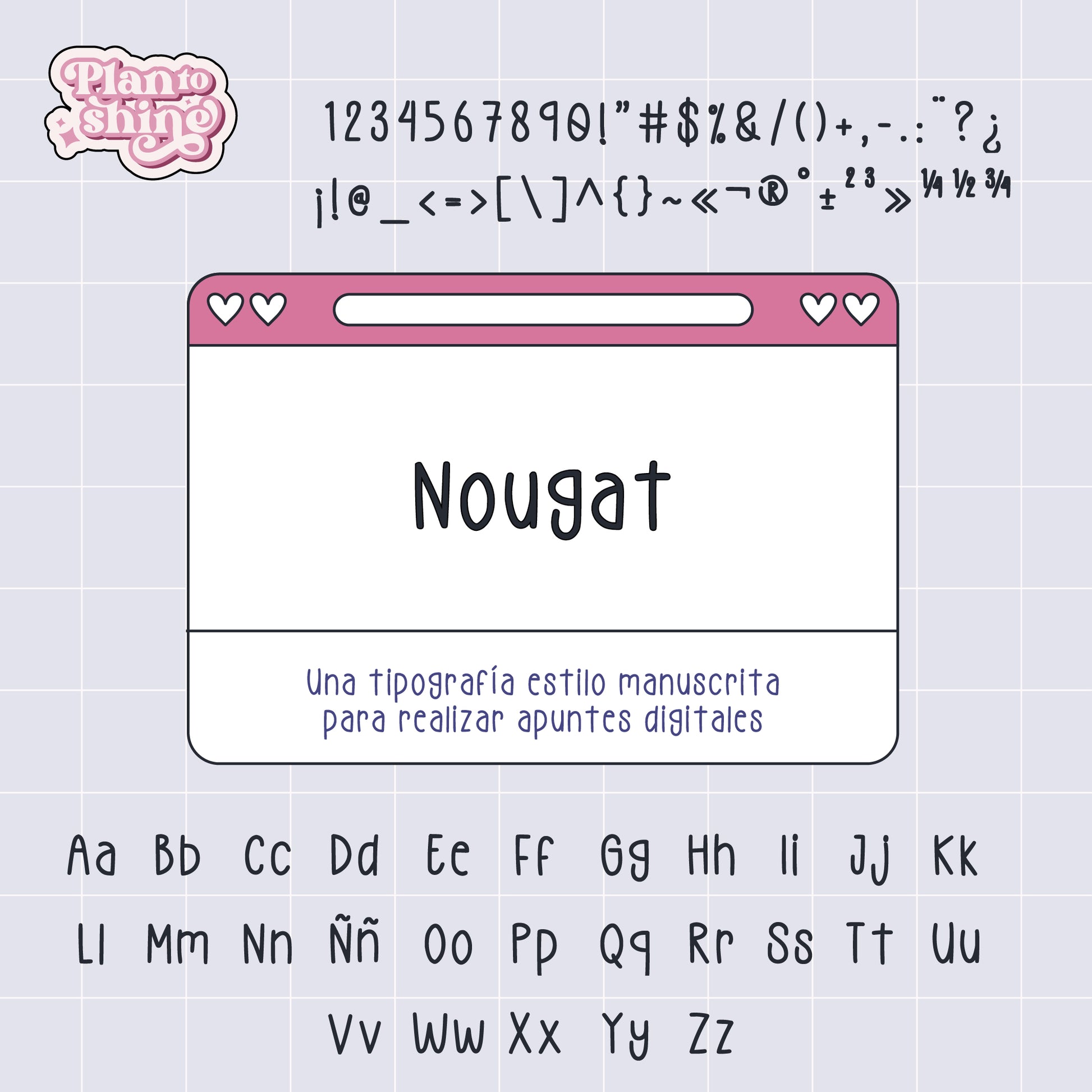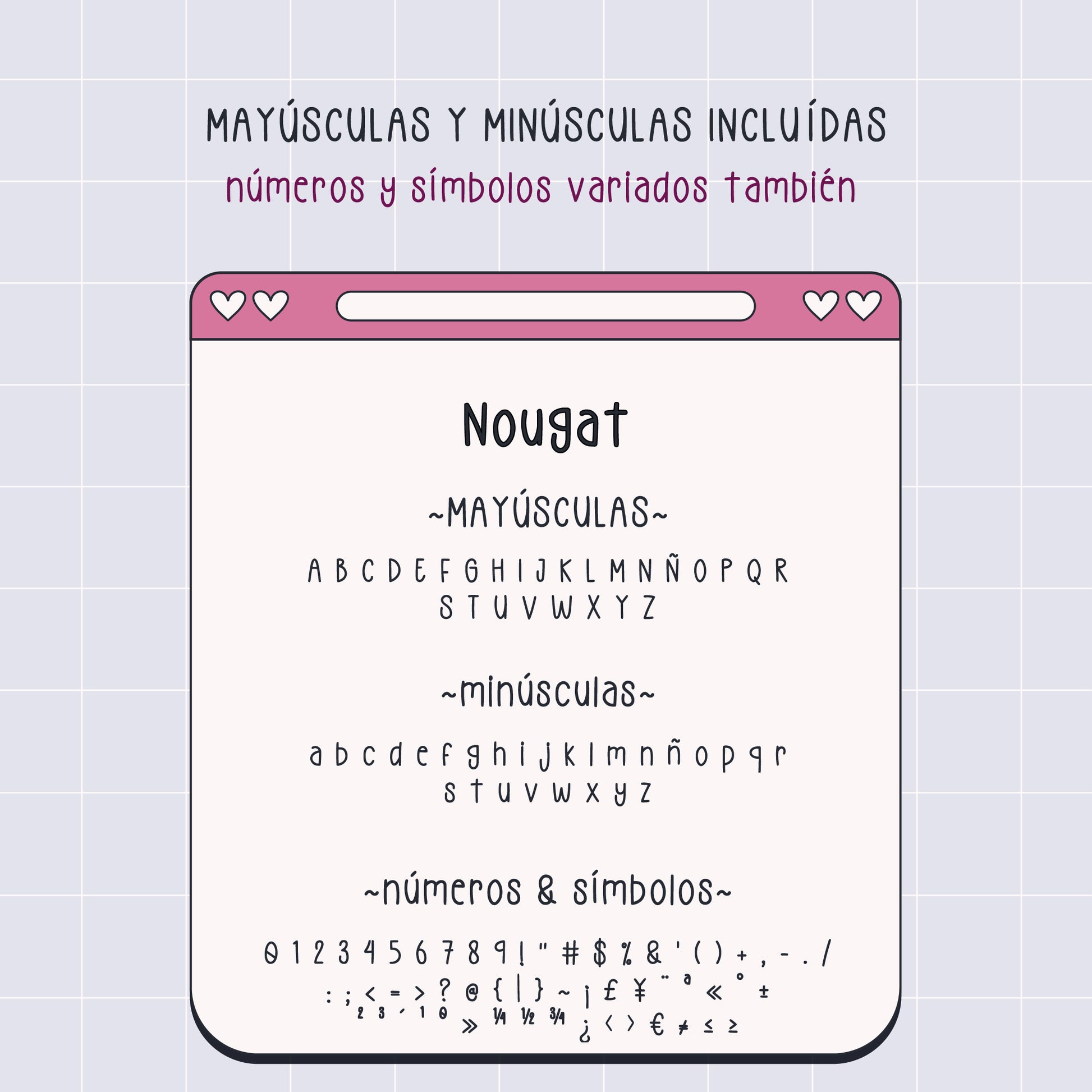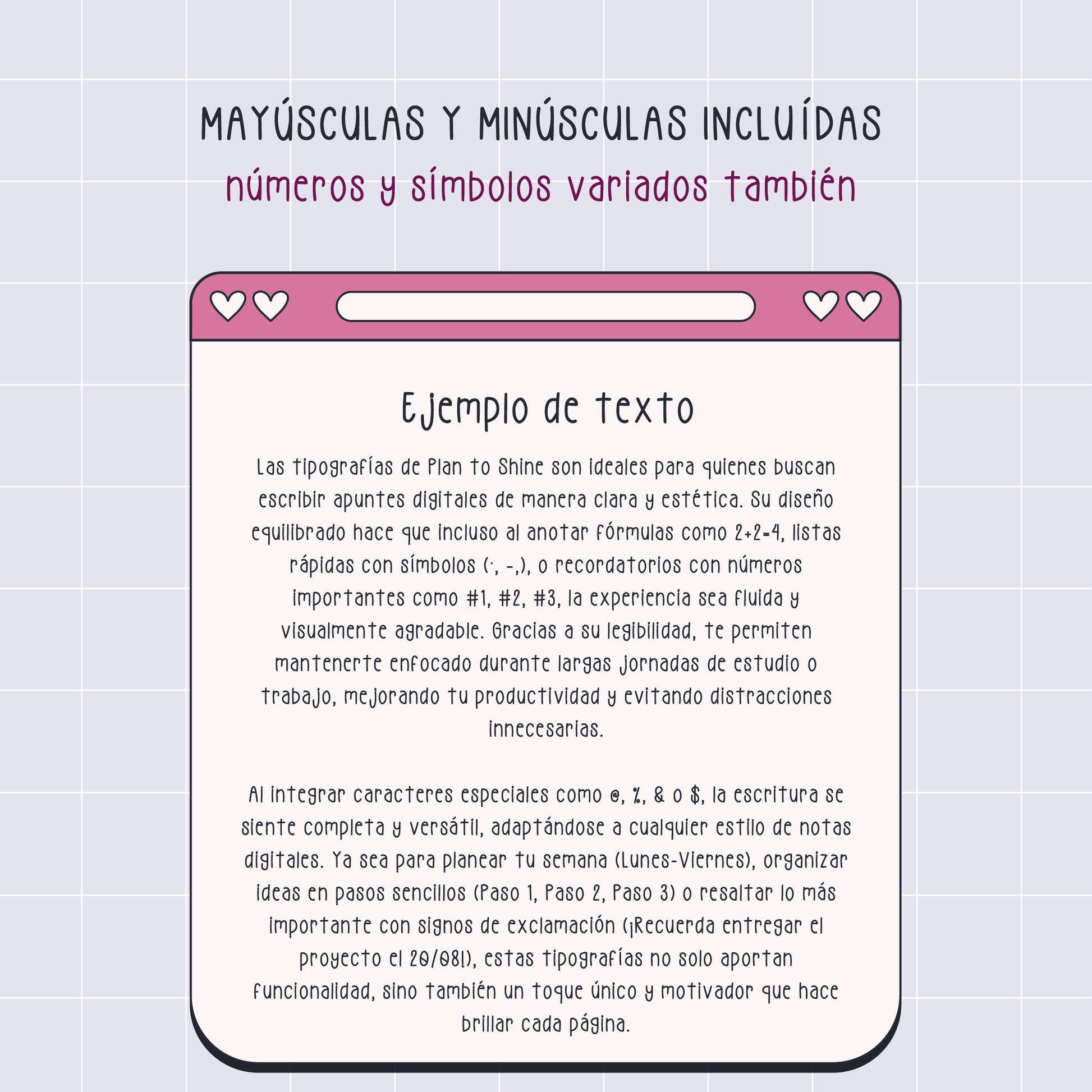
Tipografía Nougat
Nougat es una tipografía manuscrita delicada y divertida diseñada para apuntes digitales, planners y organización de estudio. Su estilo handwriting transmite un aspecto descontracturado y cercano, perfecto para dar un toque único a tus notas sin perder esa sensación manuscrita.
La fuente incluye letras mayúsculas y minúsculas, números y símbolos, lo que la hace ideal para escribir títulos, subtítulos y contenido en cuadernos digitales o aplicaciones de notas.